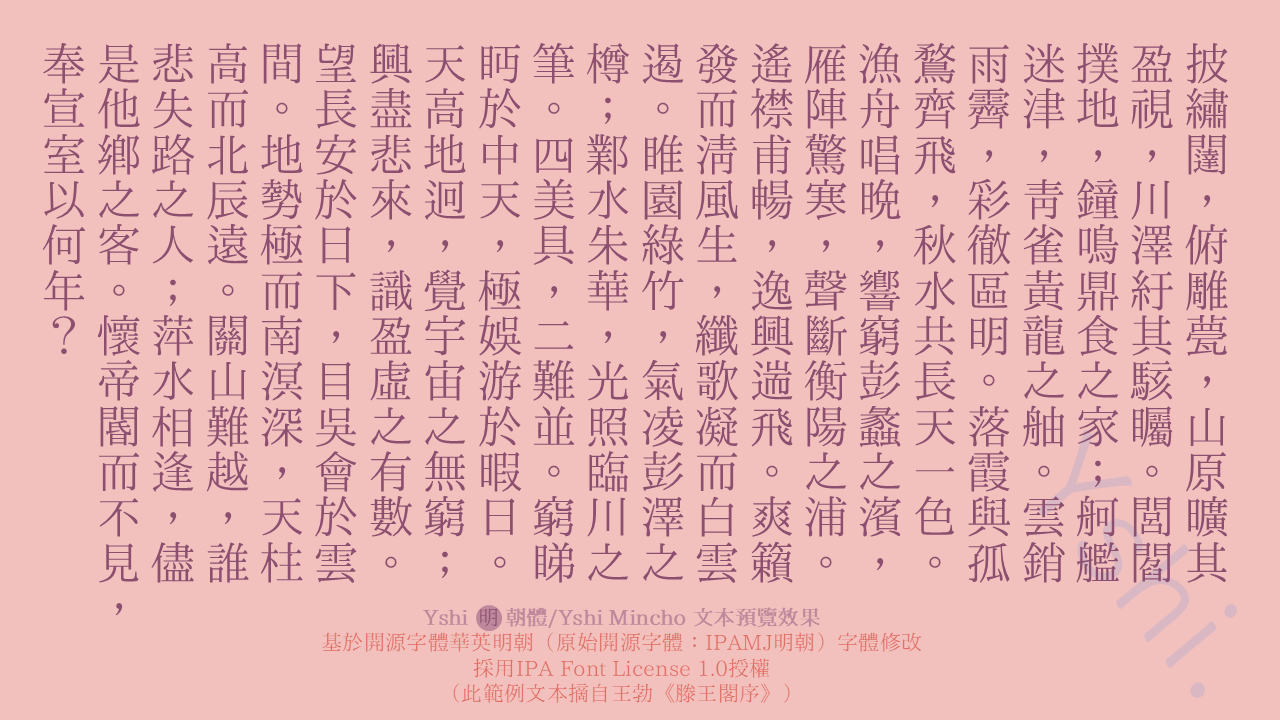
Y 式宋体
别称:Y 式宋體 / YShiMincho
概述
YShiMincho(Y式明朝体/Y式宋体)
一款衍生于“华英明朝”、“IPAmj明朝”、“霞鹜新致宋&霞鹜致宋”的字体,以旧字形笔画为主
简介
本字体是基于华英明朝、 IPAmj明朝 ,并借用一点明朝,修改的中文开源字体。字体以传统字形为主。
字符集
- IPAMJ原有字形
- 一点明朝所新增的字符,如《通用规范汉字表》收录,但IPAMJ明朝没有收的简、繁体字符以及个别方言用字
- lxgw文楷所收录汉字
- YShi笔书体收录字符(是否补全HKSCS,后续再说,本字体并未完全收录hkscs的字符)
- Adobe-JP字符(参考思源黑体JP所收录字符,个别字JMJ没收,故补充之)
- 委班复生越南所收部分喃字
注意
- 本字体着重收录汉字区,至于符号区待定
- 个别简体字由于来自于一点明朝,字形可能较为奇怪,后续计划更改、版本分流等等
- 个别字由于现成部件没有合适的比例、或者缺乏现成部件,故有些字存在机械挤压而造成粗糙,由于本人技术有限,只能略微调整、使其勉强具有美感
- 本字体并不完全符合《传承字形推荐形体表》,系个人参照之并结合诸多流传的旧字形写法,根据个人喜好取舍之
- 不计划推出多字重
- 标点符号本项目默认居中